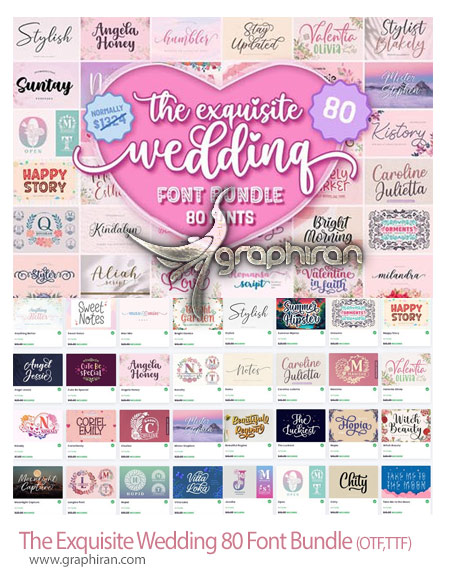
دانلود ۸۰ فونت انگلیسی عروسی The Exquisite Wedding 80 Font Bundle مجموعه ای از فونت های دستخط و دست نویس انگلیسی مناسب برای طراحی کارت دعوت عروسی و ساخت کلیپ عروسی می باشد. این مجموعه فونت خلاقانه و عاشقانه انگلیسی را می توانید از گرافیران دانلود کنید.